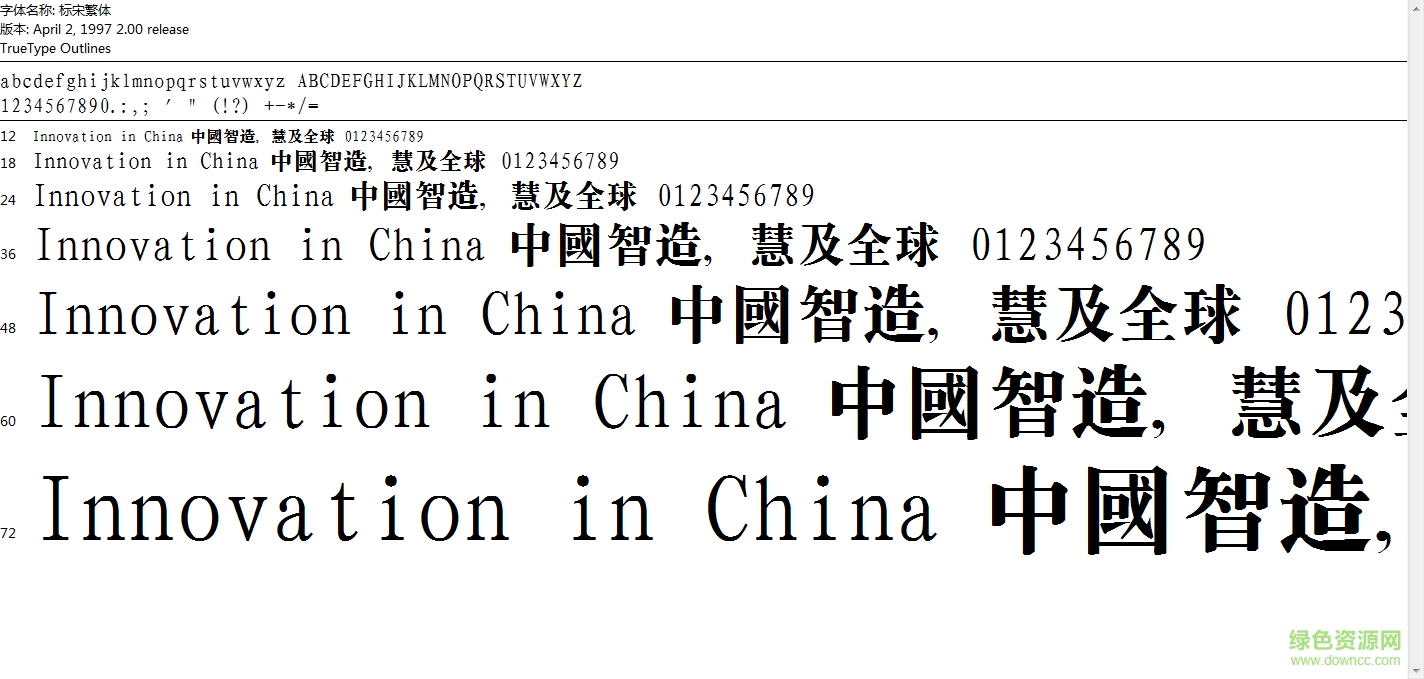
rs biaosong字体
rs_biaosong_ft字体就是标宋繁体和简体,该字体笔画粗细均匀,清秀美观,带有传统字体的韵味,可用于诗词文集、书刊正文排版等方面,需要的小伙伴快来绿色资源网下载吧!
中国文字有正、草、隶、篆、行五种。又根据各种风格,以书家的姓氏来命名,像楷书中有欧(欧阳询)体、颜(真卿)体、柳(公权)体等等。有一种字体,却不是创始人的姓氏,用朝代名来命名,这就是宋体字。
小标宋体介绍
小标宋体是《国家行政机关公文格式》中规定的一种标准字体,主要用于政府文件中的发文机关标识、公文标题和主题词词目。